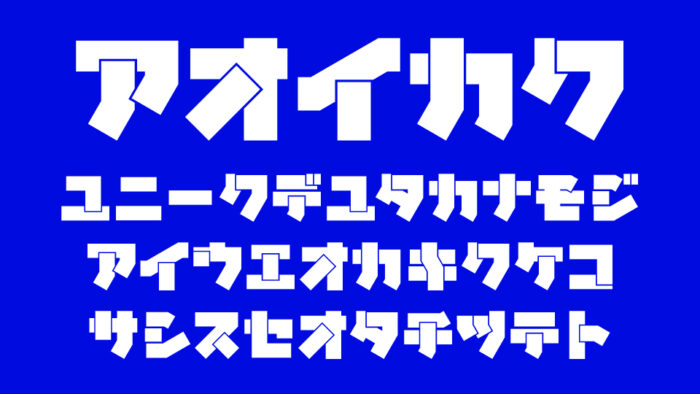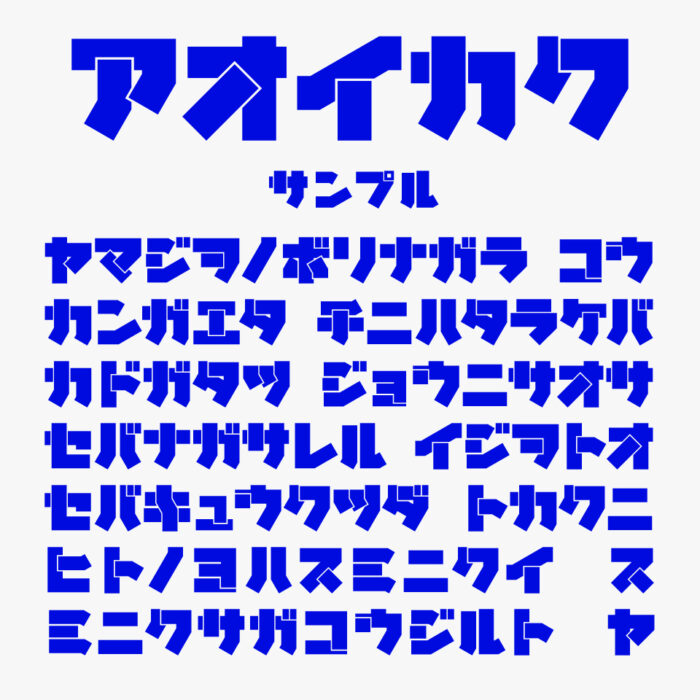
アオイカクフォントは、全体的に角張ったフォルムと幾何学的な図形が重なり合ったようにデザインされているカタカナフォントです。
直線的な極太の線にくわえて、1文字ごと文字の部位の隙間に空間が空いていて、切り絵のような、ブロックが重なってできたような不思議でカッコいいフォントです。
アオイカク
収録文字は、カタカナ・一部記号が収録されています。
ひらがな×
カタカナ○
漢字×